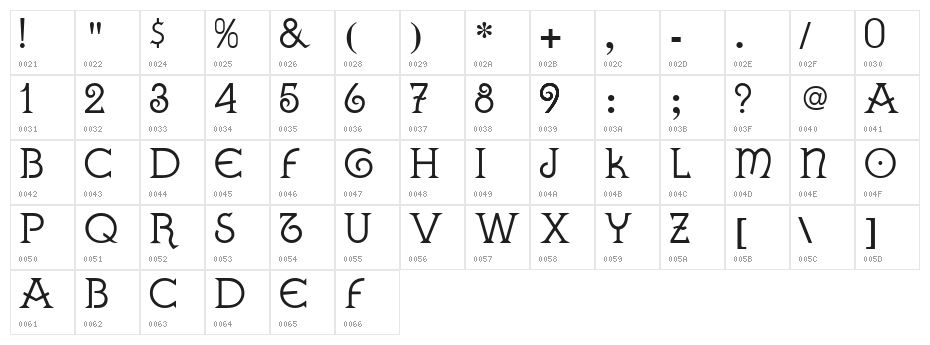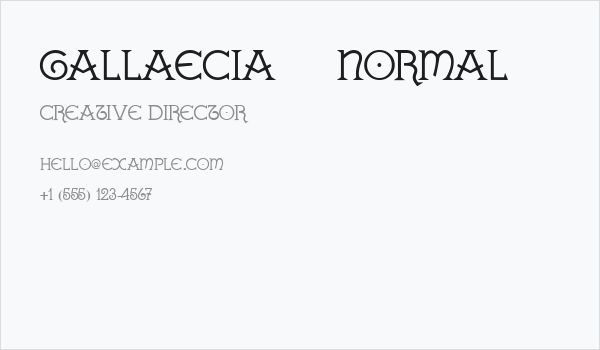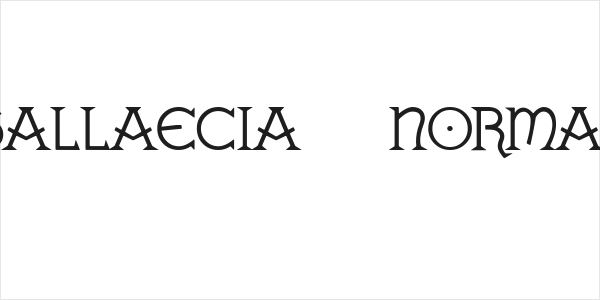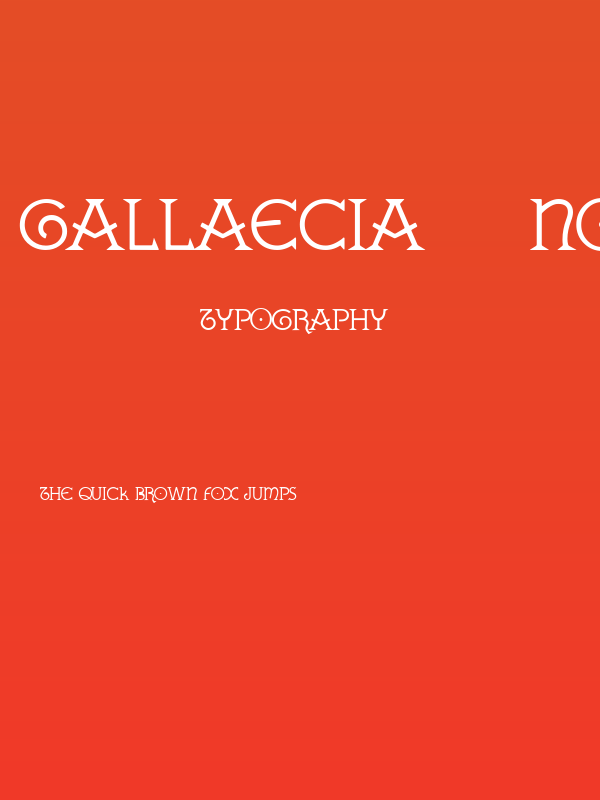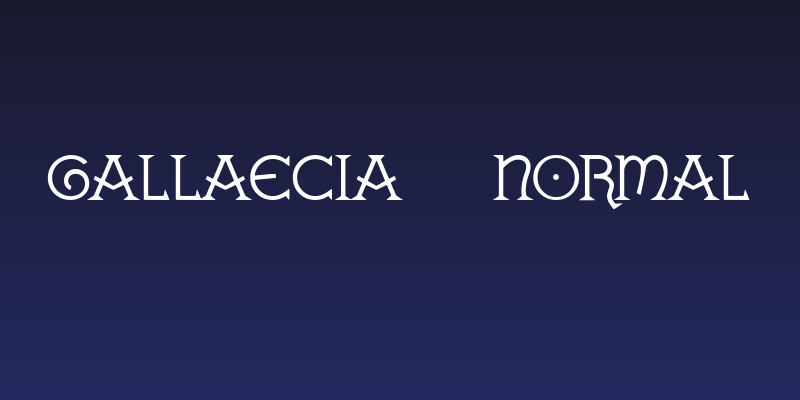
GALLAECIA Normal Font
| Kategorien | Gothic |
| Gesamtstil | Classic |
| Anwendungsfall | Headlines, Logos, Editorial design |
| Vorgeschlagene Projekte | Ideal for branding, editorial design, book covers, and creative projects that require a touch of elegance and uniqueness. |